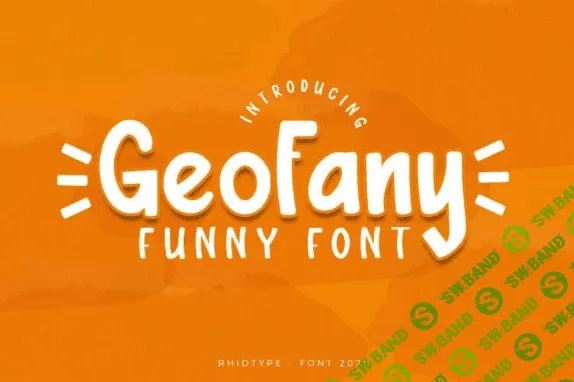
Geofanny - это забавный шрифт дисплея.
Независимо от того, используете ли вы его для крафта, цифрового дизайна, презентаций или изготовления поздравительных открыток, он идеален!